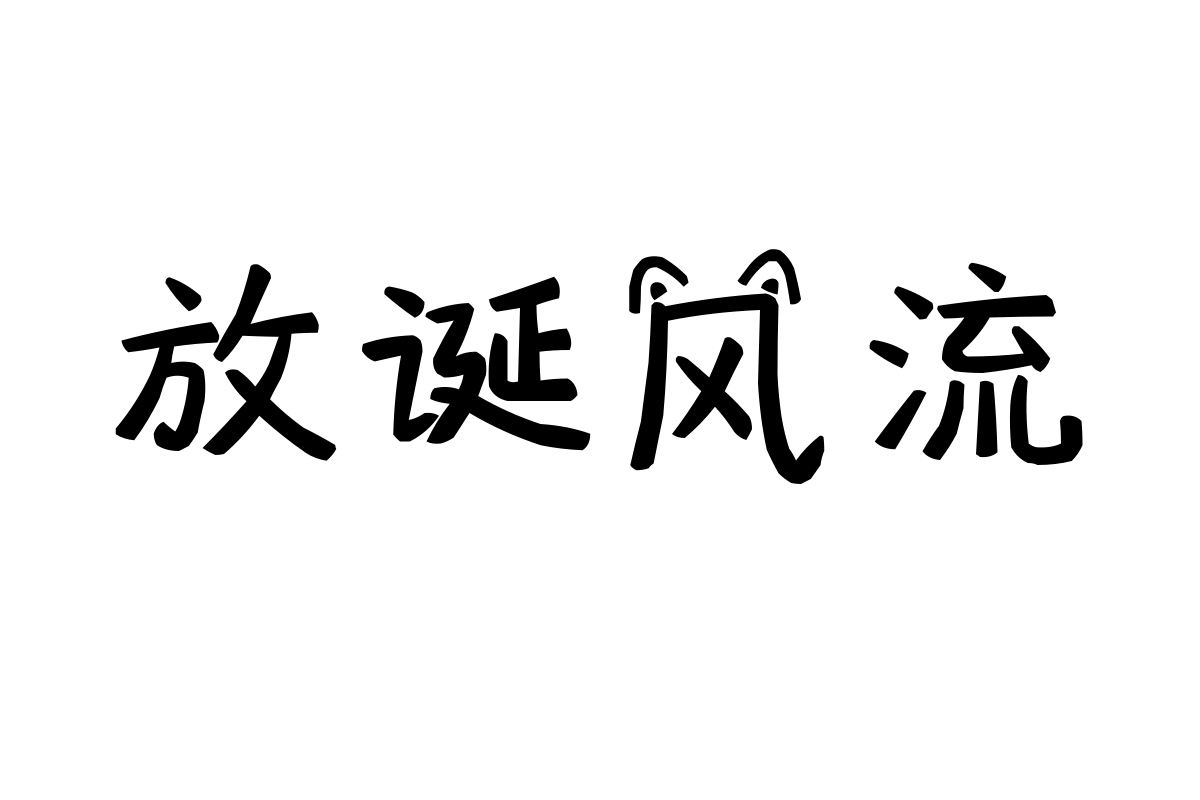
也字工厂喵喵体是一款专为喵星人设计的字体,它以其可爱的风格和独特的喵喵叫声效果而受到喜爱。这款字体具有以下特点:
1. 可爱风格:也字工厂喵喵体采用了可爱的设计风格,字形圆润,线条流畅,给人一种温馨的感觉。
2. 喵喵叫声效果:在字体中加入了喵喵叫声的效果,使得整个字体更加生动有趣。
3. 可定制性:用户可以根据自己的喜好选择不同的声音效果,还可以自定义字体的大小、颜色等参数。
4. 适用于多种场景:无论是用于宠物相关的设计项目,还是用于其他需要可爱风格的场合,也字工厂喵喵体都能满足需求。
总之,也字工厂喵喵体是一款充满创意和趣味性的字体,适合喜欢可爱风格的设计师使用。